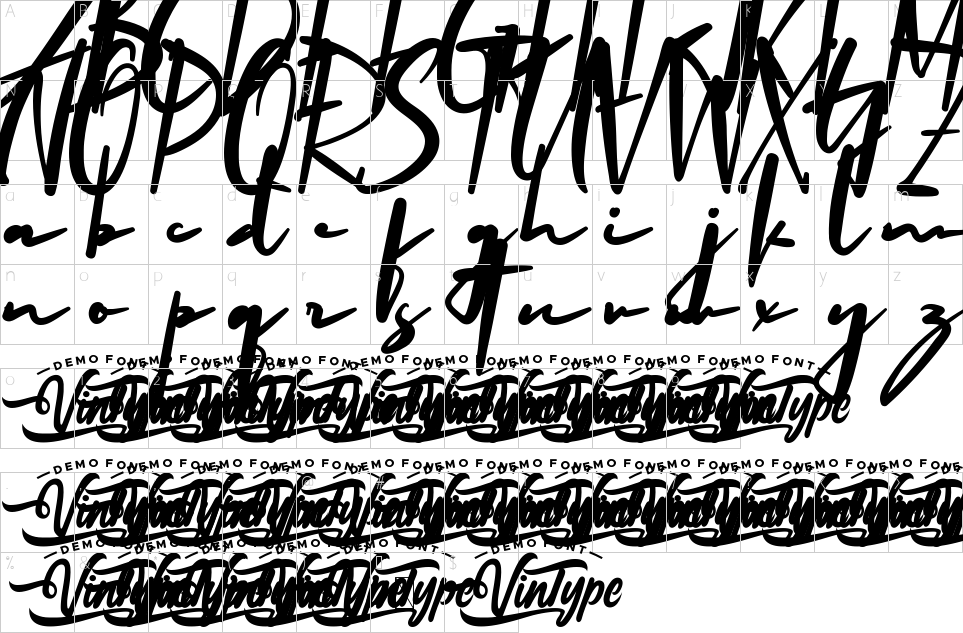
Descubra Aksarani, uma fonte única e versátil para suas criações digitais. VinType, a talentosa designer responsável por essa fonte, trabalhou arduamente para criar um estilo marcante que combina simplicidade e elegância. Download Aksarani font para Windows e Mac, disponível gratuitamente e amplamente utilizada. Mais de 600 downloads confirmam o valor deste design exclusivo, e agora você pode experimentar a Aksarani também. Seja você um designer gráfico ou um criador de sites, Aksarani pode ajudá-lo a tornar seus trabalhos mais atraentes e profissionais.